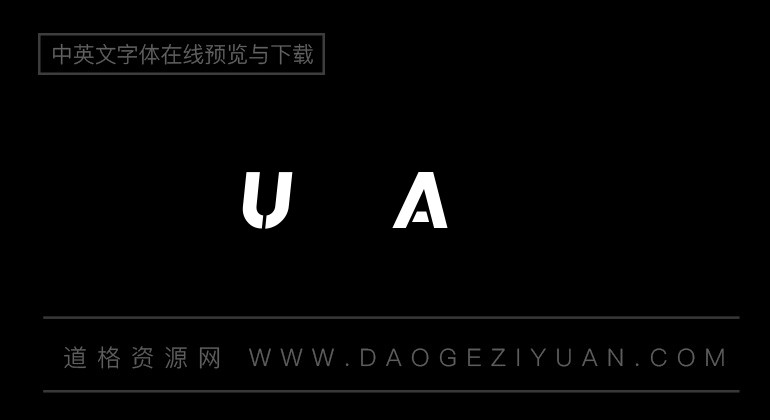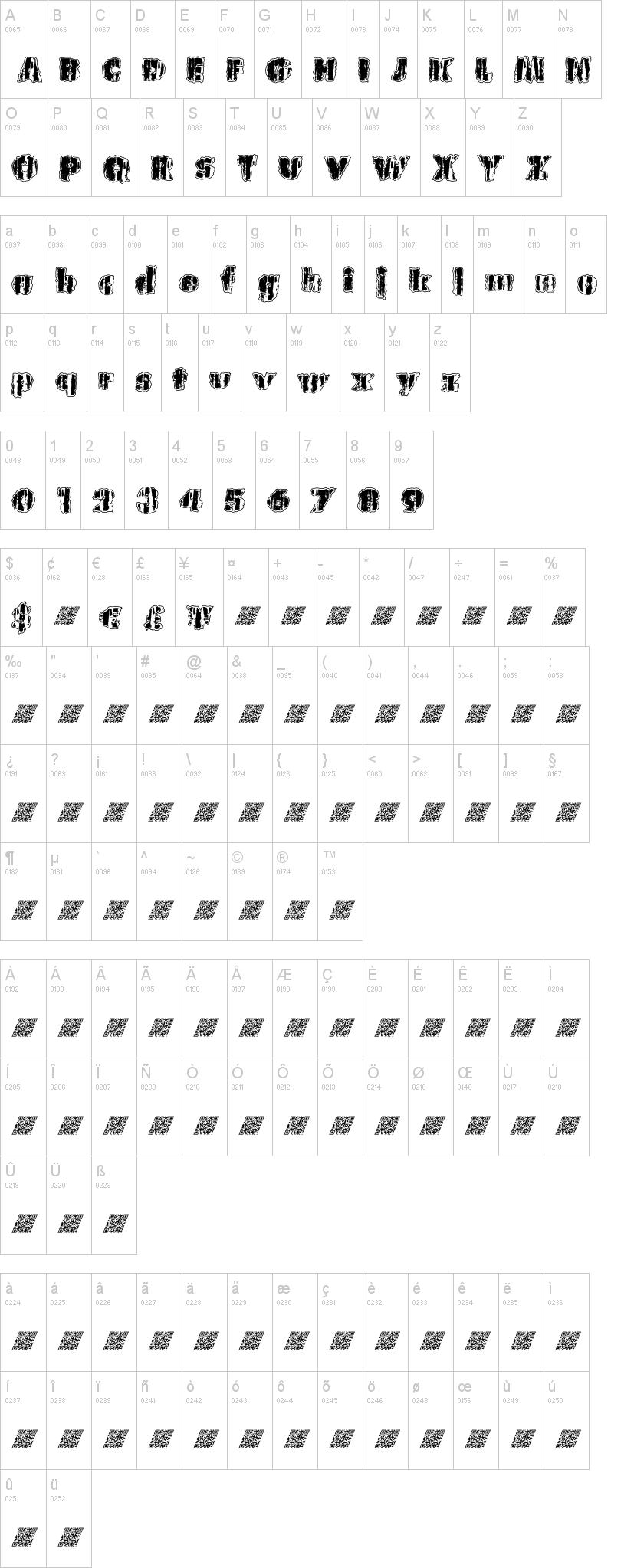
Urban Animal 是一款来自美国设计师克里斯·穆尔的现代字体。它有着独特的节奏感,细节丰富,更具有街头风格,适合用于商业、广告等场景。字体支持多种语言,有大小写字母、数字、标点符号等,可以用来制作海报、标志、印刷品等。Urban Animal 的字体比较粗犷,有着良好的可读性,可以让文字和图片更加融合,令设计更加有趣。内容介绍
Urban Animal是一款非常不错的手写艺术字体,具有很好的视觉感,适合于文化类的宣传设计、商业类品牌的广告和产品包装设计以及个性化文字排版等较多场景。